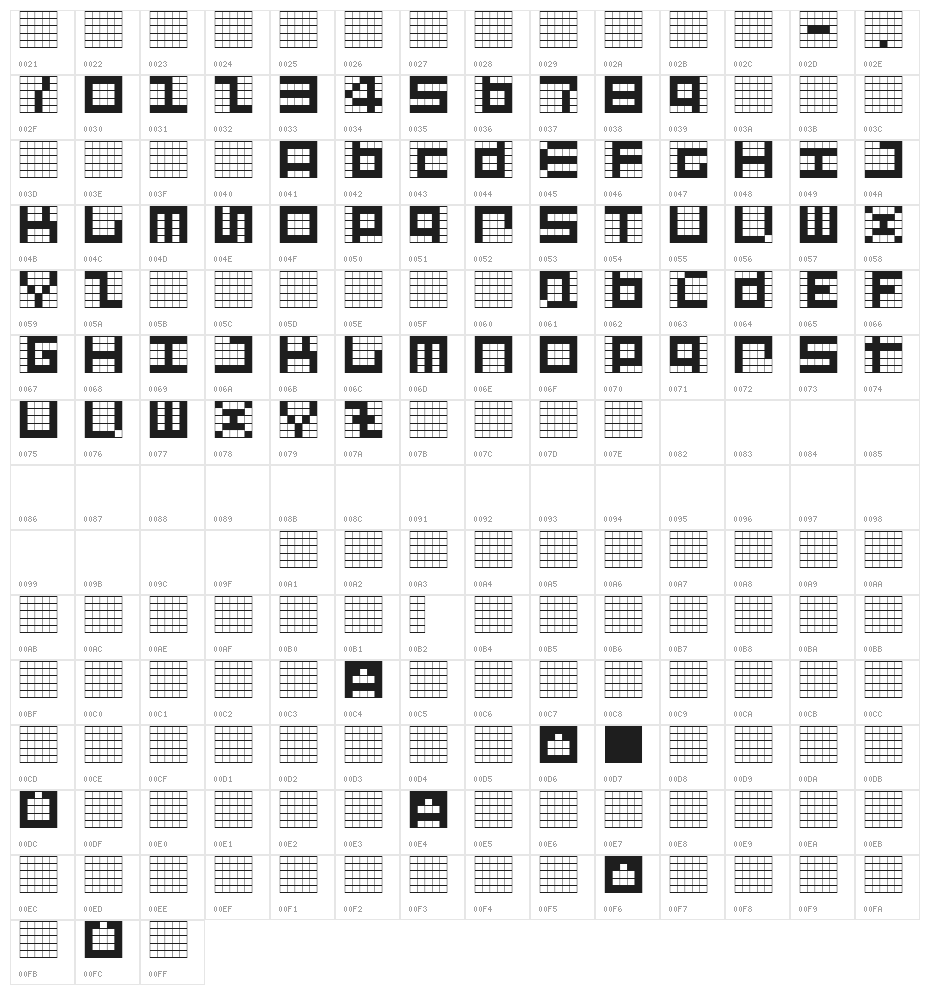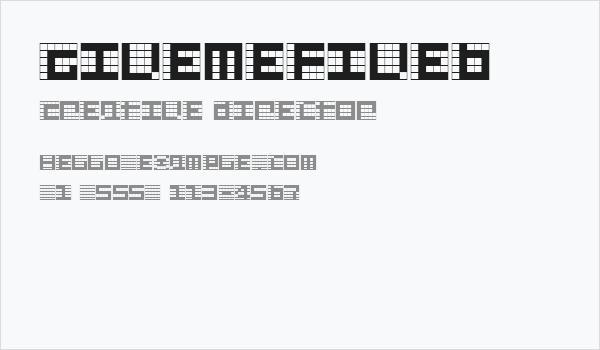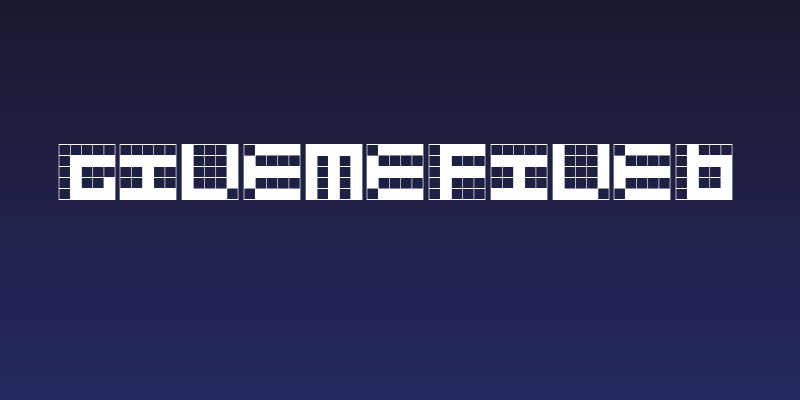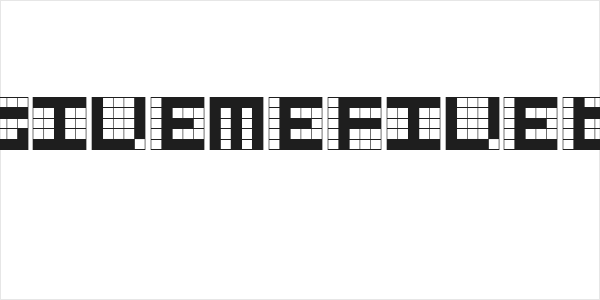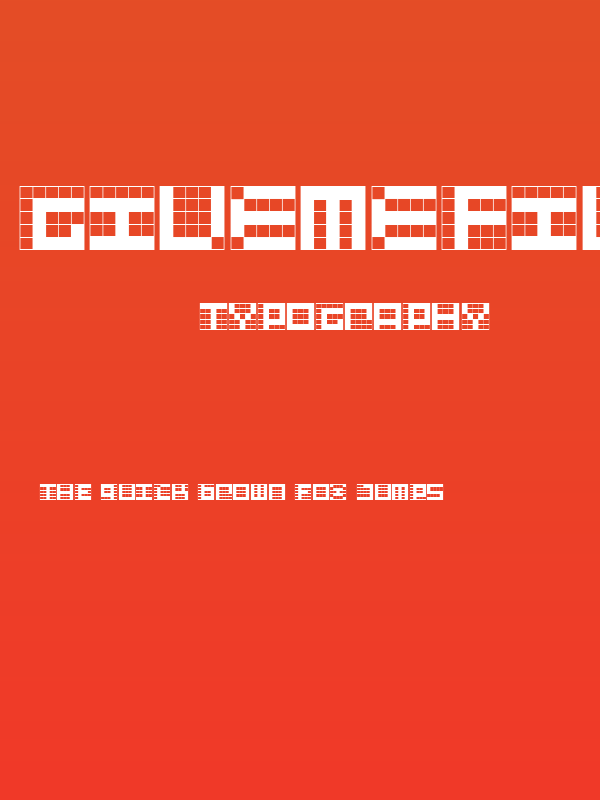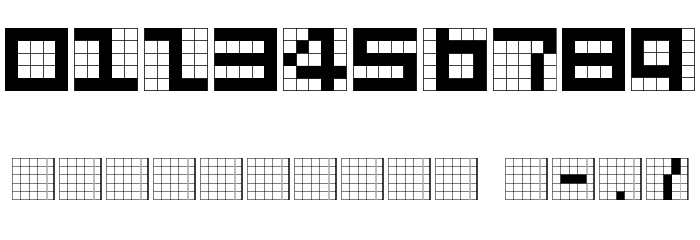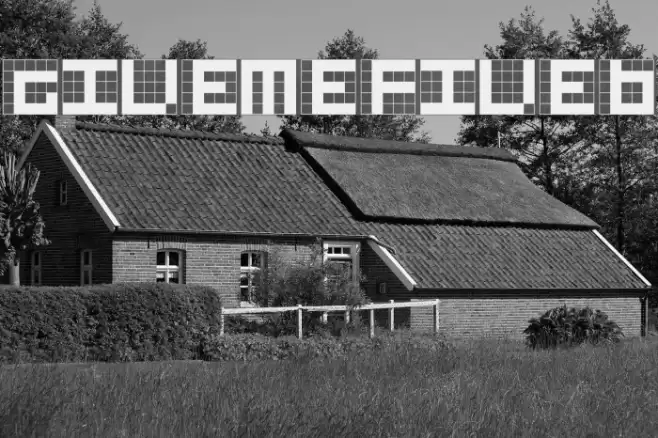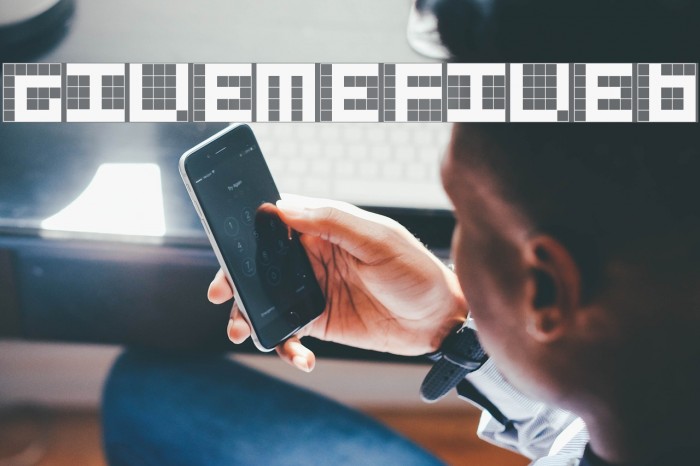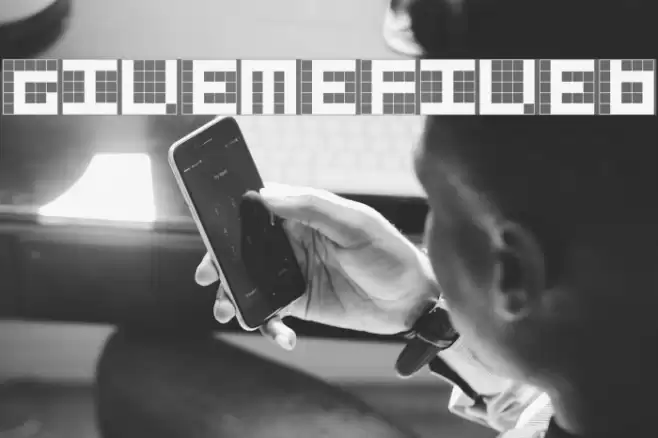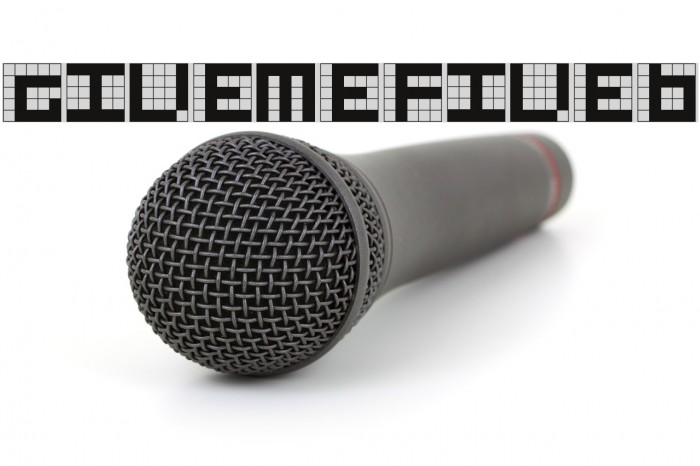
GiveMeFiveB Font
| Caso de uso | Logos, Headlines, Digital Art |
| Projetos propostos | Ideal for digital art projects, retro-themed designs, video game graphics, and tech-related branding. |